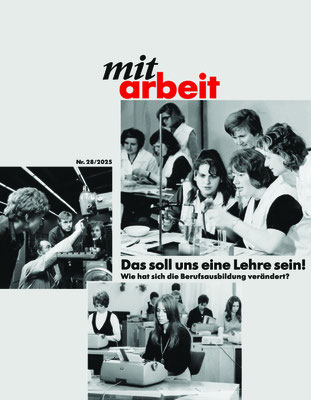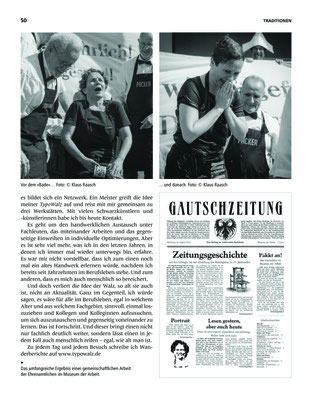
Artikel in der Ausgabe 28/2025 »Das soll uns eine Lehre sein! Wie hat sich die Berufsausbildung verändert?«
Unterwegs für das Handwerk
Alles beginnt mit der Suche nach der Hamburger Schrift und dem Sammeln von Buchstaben, was ich schon als Kind gern getan haben. Das Fotografieren von Lettern auf hanseatischen Fassaden und Stöbern in historischen Schriftmusterbüchern im Museum der Arbeit führt mich schließlich zum traditionellen Handsatz und Buchdruck. Nach dem Abschluss meines Typografie-Studiums soll es so richtig losgehen, und ich mache mich auf den Weg, das Handwerk des Schriftsetzens zu erlernen. Es sind die Bleischriften und Holzlettern, der Geruch nach Farbe und der Rhythmus der Druckmaschinen, die mich in den Bann ziehen. Will man ein vom Aussterben bedrohtes Handwerk erlernen, gibt es keine Berufsschulen oder offizielle Lehrherren mehr (...)
»Manueller Buchdruck in Hamburg
Echte Handarbeit und kleine Manufakturen sind bei manchen Menschen in Zeiten von Digitalisierung und Massenproduktion wieder sehr gefragt - und mehr Handarbeit als bei Achim Wittrin geht nicht. Ein Besuch in seinem kleinen Laden in Eppendorf ist wie eine Zeitreise ins 15. Jahrhundert, als Johannes Gutenberg mit Metalllettern und Handdruckpressen die Buchdruckkunst erfand. Seit 1977 lebt der mittlerweile 78-Jährige seine Kreativität hier aus – auch mit bedruckten Schürzen und T-Shirts mit Sprüchen wie „Und täglich grüßt das TRUMPeltier“. Er bietet u.a. Workshops, bei denen er seinen Teilnehmern die Kunst des manuellen Buchdrucks beibringt.«
Der NDR war zu Besuch in der Kleinen Letternpresse, um einen Beitrag zu unseren Workshops zu drehen: ☞ NDR Nordtour
In der Ausgabe 5 des Grafikmagazins hat Bettina Schulz einen Artikel über die Handsatzwerkstatt Fliegenkopf in München von Christa Schwarztrauber geschrieben. Während meiner Reise habe ich dort auch Station gemacht und freue mich, dass es ein weiterer Beitrag zum Erhalt der Schwarzen Kunst ist. Danke Bettina
»Vom Zwiebelfisch zum Fliegenkopf
Gott grüß die Kunst -der traditionelle Gruß unter Buchdruckern, Schrift- und Maschinensetzern sowie Lithografen existiert bereits seit 1740 und bringt auch heute noch zum Ausdruck, dass das moderne Druckgewerbe seine Wurzeln im Handwerk hat. Und so ganz ist dies bei aller Technik auch noch nicht verschwunden, wie ein Blick in die Handsatzwerkstatt Fliegenkopf zeigt ...«
Das Zeitungsprojekt
Während das Hamburger Abendblatt sein Jubiläum zur 25-jährigen Onlineausgabe ihrer Tageszeitung feiert, wird im Museum der Arbeit seit 25 Jahren traditionell gedruckt. Auch wenn das Handwerk
längst museal ist, ist es im Museum der Arbeit lebendig geblieben und wird getragen von vielen ehrenamtlichen Fachleuten. Es sind Menschen, deren Herz höherschlägt, wenn der Geruch der
Druckerschwärze durch die Gassen zieht und der Rhythmus der Monotype zum Klappern der Linotype und Schnaufen vom Heidelberger Tiegel zu Musik wird. Hier werden Inhalte noch wahrhaftig begriffen
und Wörter Buchstabe für Buchstabe von Hand zu Texten gesetzt. Um das Handwerk zu bewahren, gibt es nur noch wenige, die das Wissen und Können von den alt gewordenen Setzern und Druckern erlernen
und weitergeben wollen. Im Jubiläumsjahr 2022 entsteht eine Zeitung im traditionellen Buchdruck (...)
Sehr geehrt war ich über die Empfehlung vom italienischen Papierhersteller mich für den Fedrigoni Top Award mit dem TypoSkat und TypoBlatt für 2023 zu bewerben. Tatsächlich bin ich in der erste Vorentscheidung nominiert worden!
During my TypoWalz 2020 at the Stralsund Playing Card Factory, I set a typographic pack of 32 cards and printed a small edition on the Asbern proof press. Quickly the TypoSkat was sold out and I decided to produce a 2nd edition, with the letterpress printer Walter Fischer at the »Museum der Arbeit« in Hamburg on the Heidelberger Cylinder and then die-cut it on the Heidelberger Tiegel. On request for a typographic rummy game, I expanded the 2021 game to 58 cards, including jokers and produced the TypoBlatt once more with Walter Fischer at the »Museum der Arbeit«. Both TypoSpiele feature traditionally hand-set TypoGraphics as card images. Like the classic double images, they can be viewed from both sides, not being mirrored, but rather being designed by »text twisting«.
The playing cards and the tuck boxes were printed on Fedrigoni recycled uncoated paper.
Inschriften des 20. Jahrhunderts im Hamburger Stadtbild
Lehrende: Prof. Dr. Margit Kern
Kommentare/ Inhalte:
Der Exzellenzcluster der Universität Hamburg mit dem Titel „Understanding Written Artefacts“ analysiert Schriftartefakte aus verschiedensten kulturellen Kontexten und Jahrhunderten. Bei dem
Publikations- und Ausstellungsprojekt „Inschriften des 20. Jahrhunderts im Hamburger Stadtbild” handelt es sich um ein Projektseminar für Studierende, die sich für die Thematik des Clusters
interessieren. Dabei soll Hamburg im Zentrum stehen. Eine wichtige Beobachtung lautet, dass Schriftzüge auch in der Stadt des 20. Jahrhunderts eine zentrale Rolle spielen, da Orte sowie
Institutionen mit ihrer Hilfe besonders ausgezeichnet und
hervorgehoben werden. Zugleich sind diese Schriftzüge des 20. Jahrhunderts als Plastikschriften oder Leuchtreklamen meist nicht auf Dauer angelegt. Dennoch prägen die charakteristischen Buchstabenfolgen etwa an Kinofassaden oder Bahnhöfen unsere Erfahrung und Wahrnehmung des Stadtraums nachhaltig. Für den Ausstellungskatalog sollen Studierende Katalognummern zu ausgewählten Beispielen von Schriftartefakten verfassen (...)
Jana auf der TypoWalz
Diesen außergewöhnlich Blog legen wir Ihnen sehr ans Herz:
Die Typografin und Kommunikationsdesignerin Jana Madle-Elmerhaus hat sich auf eine Walz begeben; als »Blei-Stift«, wie sie selbst schreibt, ist sie seit 2019 wochenweise auf TypoWalz ...